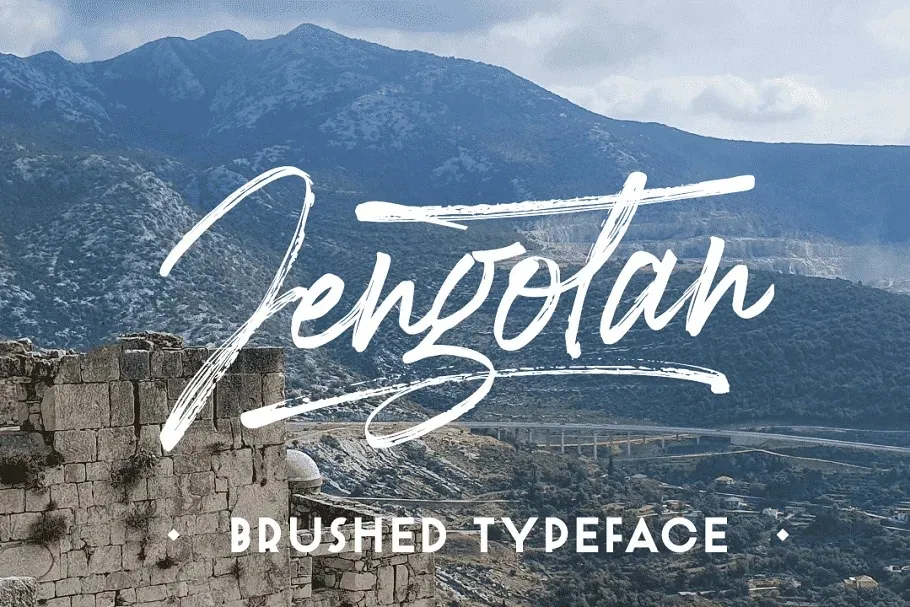
A fonte Jengotan é uma mistura vibrante de desenho e arte digital que transmite a essência do autêntico traçado artesanal. Criada pelo designer sueco Mans Greback, esta tipografia foi construída com técnicas manuais em papel antes de ser transformada em formato vetorial para aparecer perfeitamente no ambiente digital. O resultado é um estilo aparentemente natural, cheio de textura e imperfeições, que transmite a dinâmica da escrita à mão livre. Essa característica faz dela uma escolha ideal para projetos que exigem autenticidade e personalização única, permitindo-lhe se destacar em qualquer mídia digital onde seja aplicada. Jengotan é perfeita para aqueles que procuram uma fonte script capaz de dar vida a seus trabalhos criativos de forma autêntica.